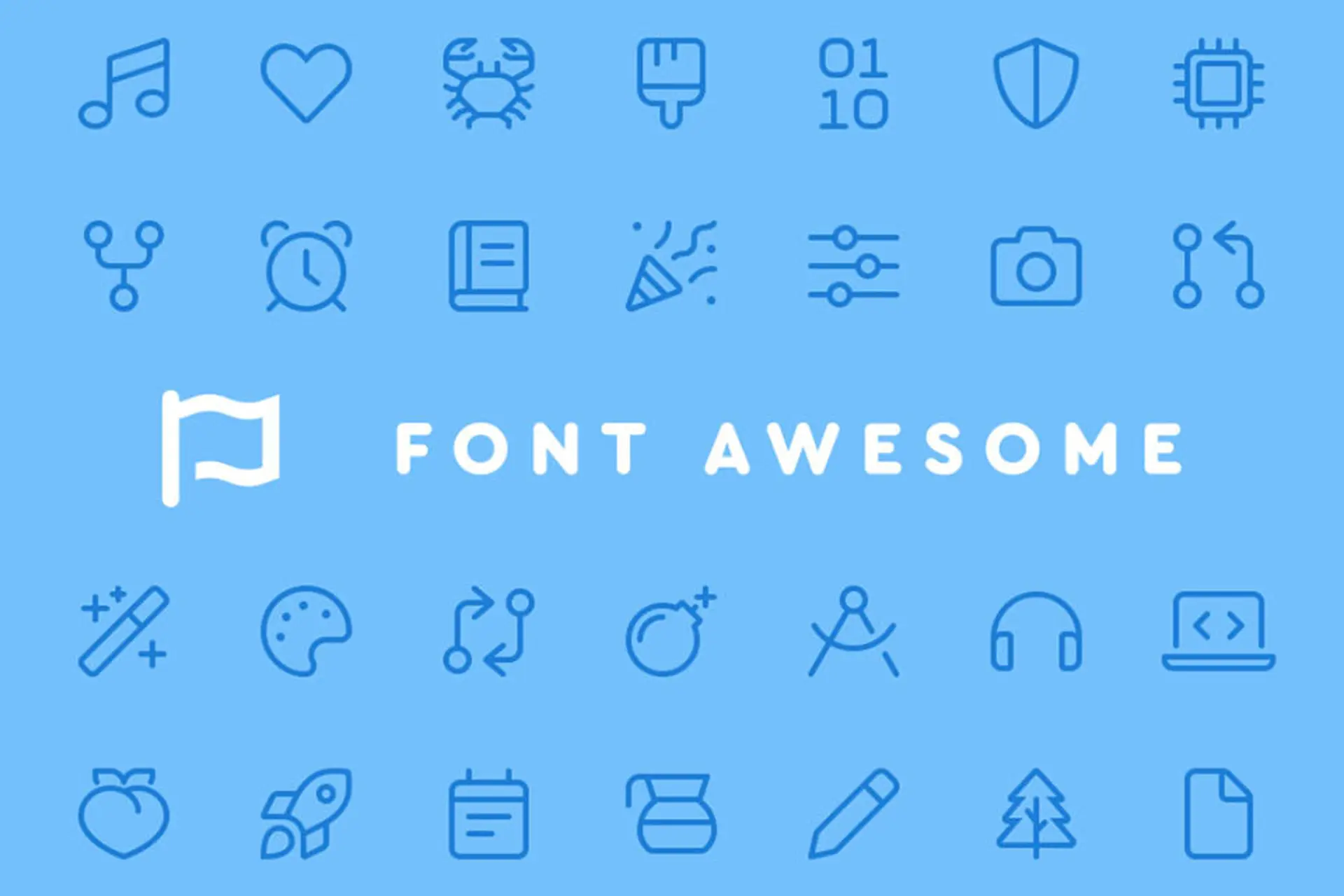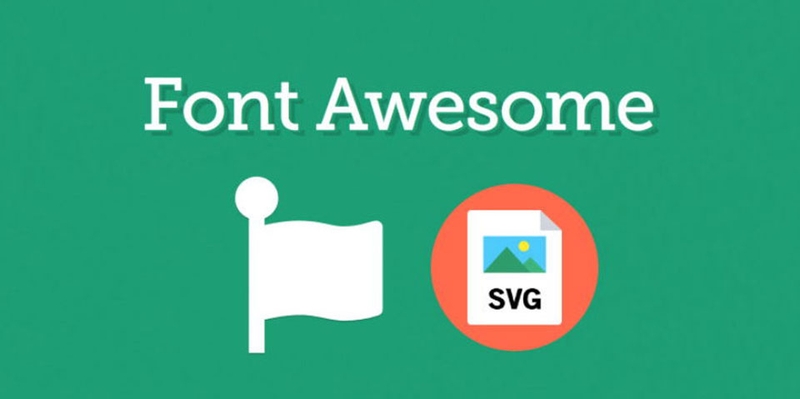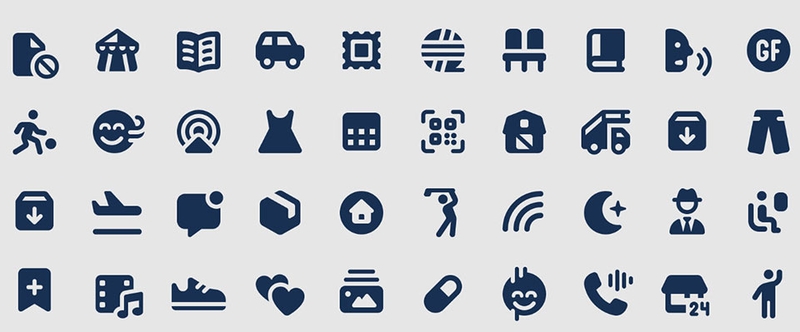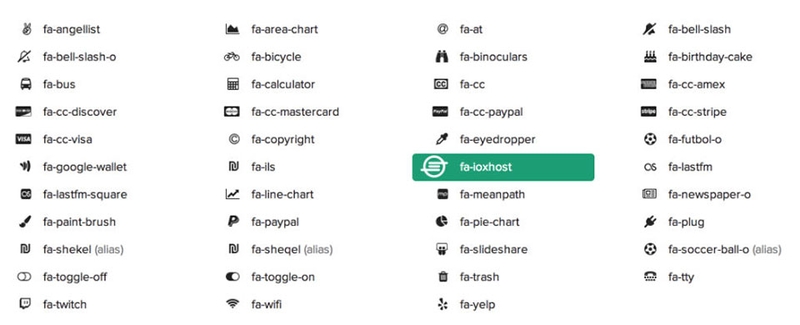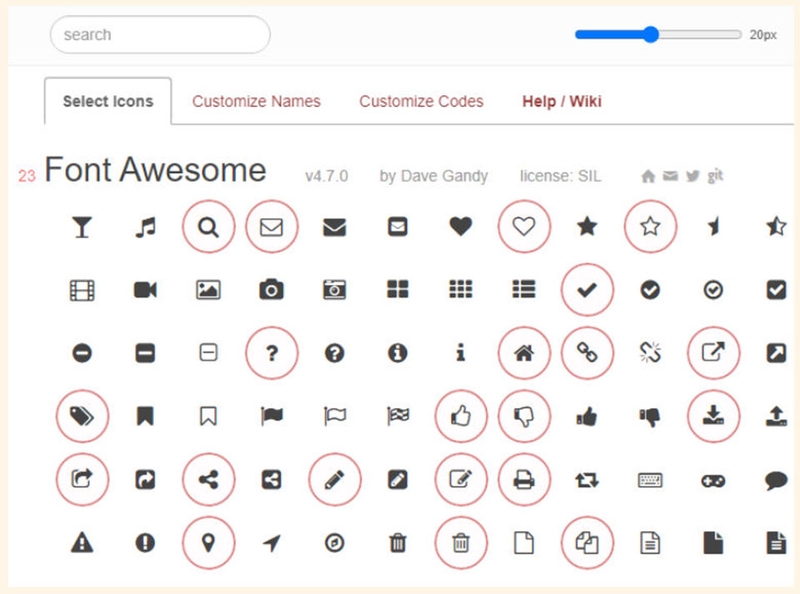
Khám phá Font Awesome: Bộ icon mạnh mẽ giúp website đẹp, hiện đại và chuyên nghiệp hơn
Nhìn chung, Font Awesome nổi bật không chỉ vì nhiều icon, mà vì nó kết hợp được quy mô thư viện lớn, khả năng tích hợp rộng, mức tùy biến cao và hiệu năng ngày càng tốt hơn. Nếu bạn đang tìm một thư viện icon đẹp, dễ dùng và phù hợp với nhiều loại website, thì đây là một lựa chọn rất đáng cân nhắc.
Tổng quan về Font Awesome
Những ưu điểm nổi bật của Font Awesome
Tạm kết
Một website đẹp không chỉ nằm ở màu sắc hay bố cục, mà còn được tạo nên từ những chi tiết rất nhỏ như icon. Chỉ cần dùng đúng icon, giao diện sẽ có thể trở nên trực quan hơn, dễ nhìn hơn và chuyên nghiệp hơn rất nhiều. Đó cũng là lý do Font Awesome ngày càng được nhiều lập trình viên, designer và chủ website lựa chọn khi muốn nâng tầm trải nghiệm người dùng mà không cần tốn quá nhiều thời gian thiết kế.
Vậy Font Awesome là gì? Vì sao bộ icon này lại phổ biến đến vậy? Chúng ta hãy cùng khám phá ngay trong bài viết dưới đây.
Tổng quan về Font Awesome
Font Awesome là một thư viện icon và toolkit rất quen thuộc với giới thiết kế và lập trình web. Điểm hấp dẫn của công cụ này nằm ở chỗ nó giúp bạn thêm các biểu tượng đẹp, rõ ràng và đồng bộ vào website chỉ với vài dòng mã, đồng thời vẫn cho phép tùy biến linh hoạt về kích thước, màu sắc, hiệu ứng và cách hiển thị.
Font Awesome - 02
Ở thời điểm hiện tại, Font Awesome vẫn là một trong những bộ icon phổ biến nhất. Nó đang phát triển trên phiên bản Font Awesome 7, hỗ trợ rất nhiều kiểu icon, nhiều nhóm danh mục và nhiều cách triển khai cho web, desktop lẫn API. Dưới đây là một vài thông tin nhanh về toolkit này:
• Thể loại: Thư viện icon vector và toolkit hỗ trợ thiết kế, phát triển giao diện website/app.
Những ưu điểm nổi bật của Font Awesome
Có thể nói, Font Awesome không chỉ là một bộ icon đơn thuần. Đây là một toolkit khá toàn diện cho website và giao diện số. Dưới đây là những lý do khiến nền tảng này luôn giữ được sức hút mạnh với designer và developer.
1. Kho icon cực lớn, đa dạng style
Ưu điểm nổi bật đầu tiên của Font Awesome nằm ở độ phong phú của thư viện icon. Khi làm website, người dùng thường không chỉ cần vài icon cơ bản như menu, tìm kiếm hay giỏ hàng, mà còn cần thêm icon cho doanh nghiệp, mạng xã hội, điều hướng, biểu mẫu, dashboard hoặc landing page.
Với 64.647 icon trải rộng trong 68 danh mục và 31 style, Font Awesome giúp bạn có nhiều lựa chọn hơn trong cùng một hệ sinh thái, nhờ đó giao diện dễ đồng bộ và chuyên nghiệp hơn.
Font Awesome - 03
Không dừng lại ở số lượng, Font Awesome còn hỗ trợ nhiều họ style như Classic, Duotone, Sharp, Sharp Duotone và Brands. Một số style miễn phí, trong khi các style nâng cao thuộc gói Pro hoặc Pro+.
Điều này giúp người dùng linh hoạt hơn trong việc chọn phong cách icon phù hợp với tinh thần của từng dự án, từ giao diện tối giản, hiện đại đến những thiết kế giàu điểm nhấn thị giác hơn.
2. Dễ tích hợp, triển khai nhanh trên nhiều môi trường phát triển
Một điểm cộng rất lớn khác của Font Awesome là khả năng triển khai đơn giản và tương thích rộng. Theo tài liệu chính thức, nền tảng này hỗ trợ thiết lập trên web rất nhanh, đồng thời có hướng dẫn rõ ràng cho các môi trường phổ biến như React, kèm các gói SVG và JavaScript riêng để nhà phát triển đưa icon vào dự án theo đúng cấu trúc đang sử dụng.
Với React, thành phần React-Fontawesome còn được Font Awesome hỗ trợ chính thức cho React 16.3 trở lên, cho thấy mức độ tương thích khá rõ ràng và thực tế.
Font Awesome - 04
Ngoài web, tài liệu chính thức cũng cho thấy Font Awesome còn có thể dùng trong desktop design apps như Figma hoặc Illustrator, đồng thời có các API phục vụ nhu cầu phát triển sâu hơn.
Nhờ đó, một bộ icon có thể được dùng xuyên suốt từ giai đoạn thiết kế giao diện đến lúc lập trình và hoàn thiện sản phẩm. Với các đội ngũ muốn giữ tính nhất quán giữa design và development, đây là một lợi thế rất đáng giá.
3. Tùy biến linh hoạt
Nếu chỉ nhiều icon thôi thì vẫn chưa đủ để tạo ra trải nghiệm tốt. Điểm khiến Font Awesome được ưa chuộng lâu dài nằm ở khả năng tùy biến rất linh hoạt. Theo đó, người dùng có thể chỉnh kích thước, xoay, animate, stack, mask, layer, thêm text hoặc counter, đồng thời tiếp tục tùy chỉnh sâu hơn bằng CSS Custom Properties.
Nhờ đó, cùng một icon nhưng bạn vẫn có thể biến hóa để phù hợp với nút bấm, menu, banner, danh sách tính năng hay phần CTA trên website.